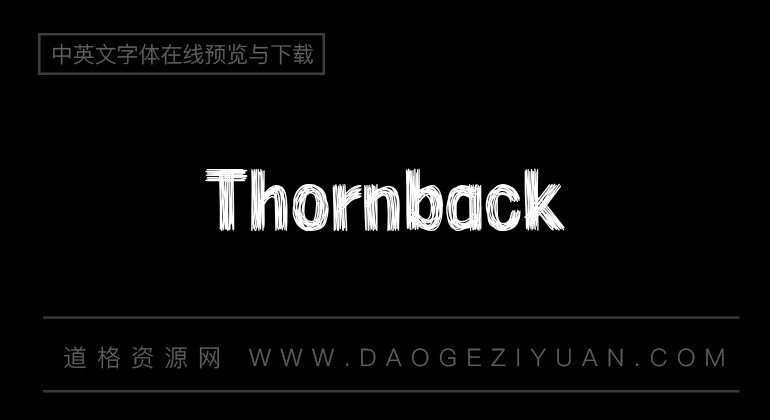
Thornback
? Thornback 字体是一款由英国设计师Rob Clarke设计的手写体字体,它的特点是具有温暖的笔触和柔和的视觉风格,可以带来温暖的感觉,是一款比较适合用于报刊,书籍,信件和其他文字类的设计中的字体。它的字形特点是有较大的空间,字体中的每个字母都有一个清晰的结构,使用它可以增加文本的可读性,同时也能把文字设计变得更加精致。
Thornback是一款非常不错的手写艺术字体,具有很好的视觉感,适合于文化类的宣传设计、商业类品牌的广告和产品包装设计以及个性化文字排版等较多场景。